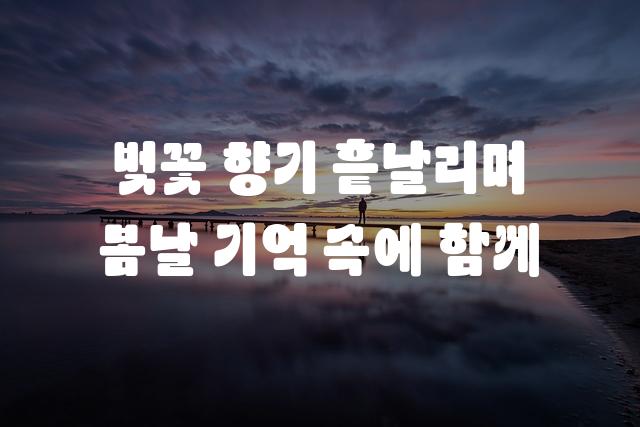
HS산토끼체2.0은 토끼네활자공장에서 제작한 한글 폰트로, 장식체의 동글동글한 꼬인 글자가 특징입니다. 이 폰트는 감성적인 느낌을 자아내며 디자인에 유니크함을 더합니다.
HS산토끼체2.0은(는)
부드러움, 복실복실, 별모양/패턴, 둥근 스타일, 자연감성, 게임 느낌, 감성적인, 장식 스타일, 꼬임/입체감 계열의 생김새를 가지고 있으며
어린이 책, 소셜 미디어, 인사말 카드 등에서 자주 활용되며, 효과적인 메시지 전달에 적합합니다.
이 폰트는 문화/예술, 이벤트/웨딩, 유아/가족 분야에 잘 어울리며,
재미있는, 귀여운, 친근한 느낌을 담고 있는 것이 특징입니다.